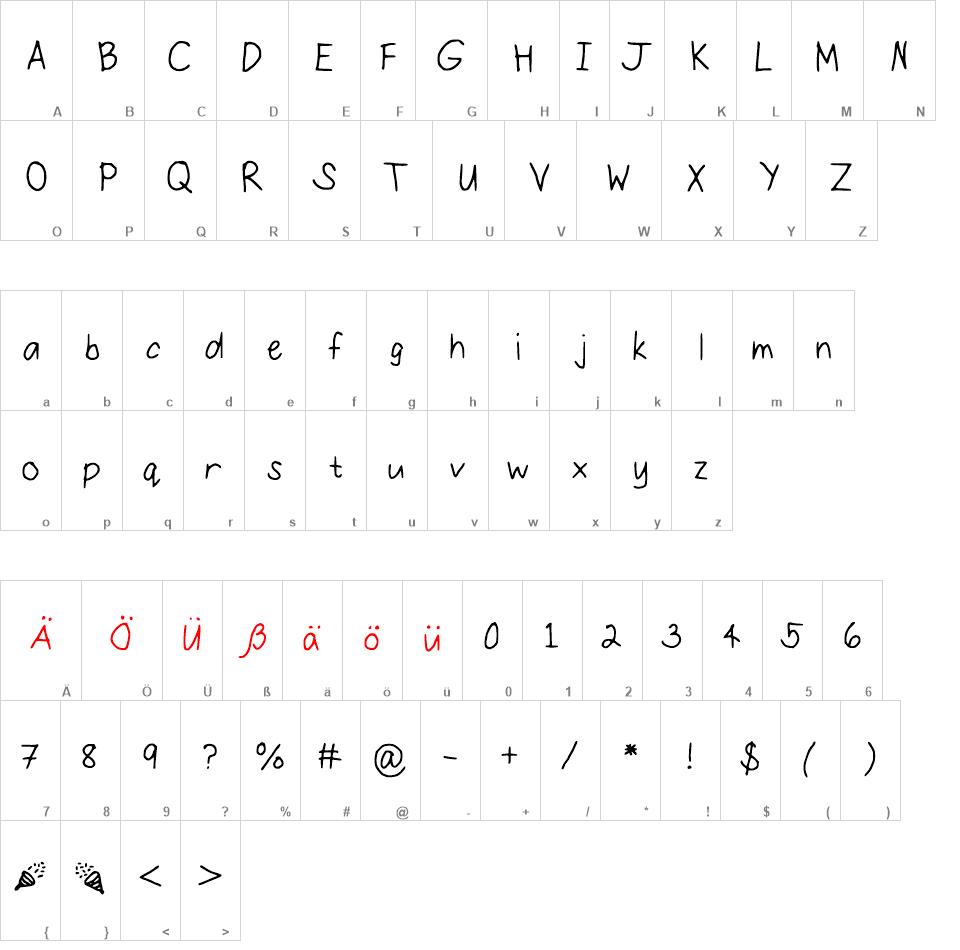
Confetti Falling
Anyhoo, Confetti Falling ist eine niedliche, von Bleistiften gezeichnete Schrift. Und ich bin heute ein bisschen fleißig geworden, also habe ich französische Charaktere mit einbezogen! Vergessen Sie nicht die Kritzeleien, die auch im Paket enthalten sind.